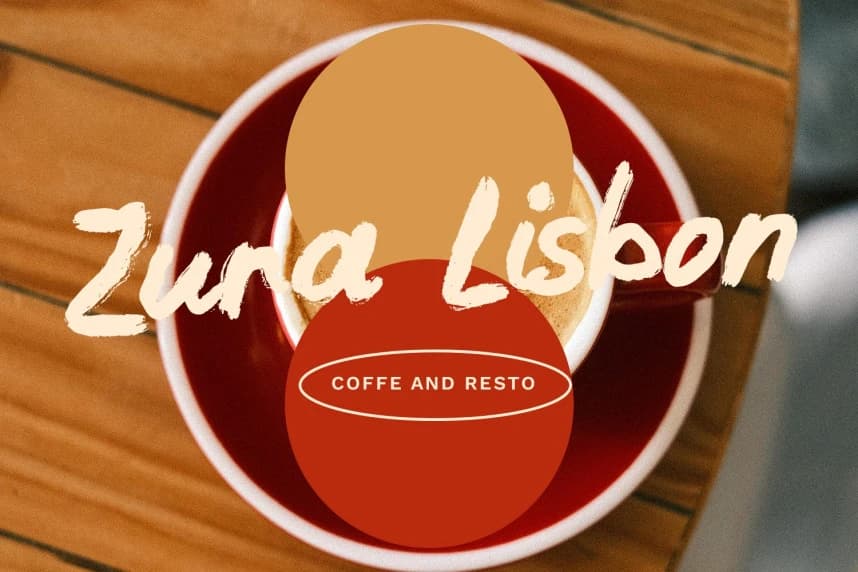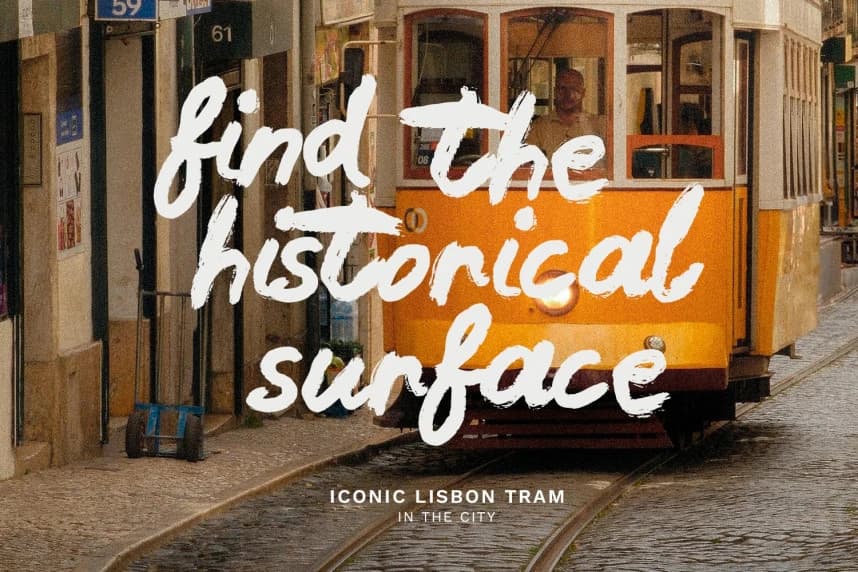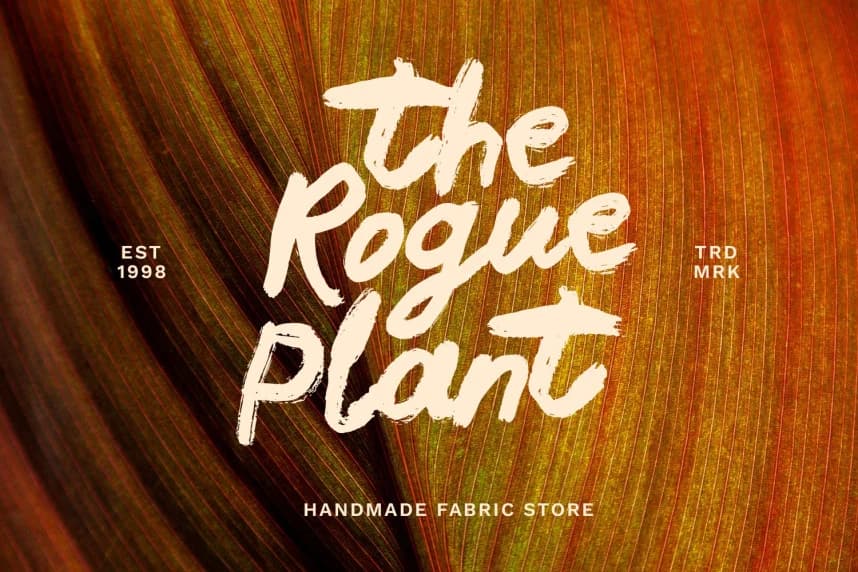
Mantis Love Font
Mantis Love Font, organik el hareketlerinden ve otantik mürekkep dokularından ilham alan doğal bir fırça fontudur. Ham his veren ama dengeli bir tasarıma sahip olan bu font, el yapımı bir karakter sunar ve markalaşma, afişler, sosyal medya ve yaratıcı başlıklar için harika çalışır.
Mantis Love Font, organik el çizgilerinden ve otantik mürekkep dokularından ilham veren doğal bir fırça yazı tipidir. Ham ama dengeli hissettirecek şekilde tasarlandı; bu yazı tipi markalaşma, afişler, sosyal medya ve yaratıcı başlıklar için harika bir el yapımı karakter sunar.
Mantis Love
Mantis Love Regular